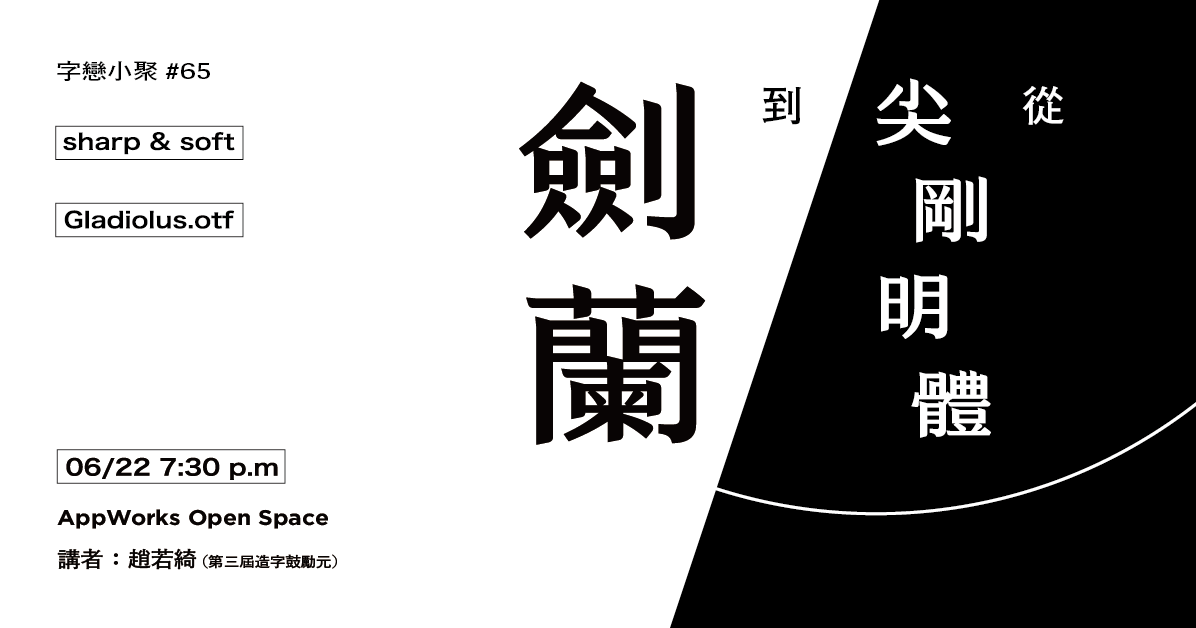
暫別許久終於復辦的字戀小聚,
當然得有個配得上的亮點主題。
經過了將近一年的學習與磨練,
終於,第三屆造字鼓勵元若綺
帶著劍蘭體來和大家見面了!
關於造字途中的辛酸和成就感,
將在小聚中一五一十與你分享。
關於劍蘭
社運的字體一定得是粗黑體嗎?或許「大聲」不只有一種做法,也不是唯一的目的。
劍蘭的構想來自社會運動的標語。許多設計師都曾挑戰此一題目,例如林芳平創作的激燃體。趙若綺的思考方式比較不一樣。既然「又粗又滿」的策略已經有人做過了,她想反向操作:讓字看起來更正經、嚴肅,引發思考,但避免強迫別人接受自己看法的凌厲感。取名「劍蘭」是為了點亮這個意圖。
嶺東科大視覺傳達系應屆畢,過去從未想過有一天會埋首字型設計。大二標準字設計,開啟了若綺的字體之眼,並擅長從街道與日常議題中獲取靈感。因希望能有額外管道精進字體設計,最終成為了第三屆造字鼓勵元的獲選作品。除了從尖剛明體發展而來的「劍蘭體」之外,所參與的畢業製作「字遊結社」亦獲得本屆「金點新秀設計獎」視覺傳達類獎項。